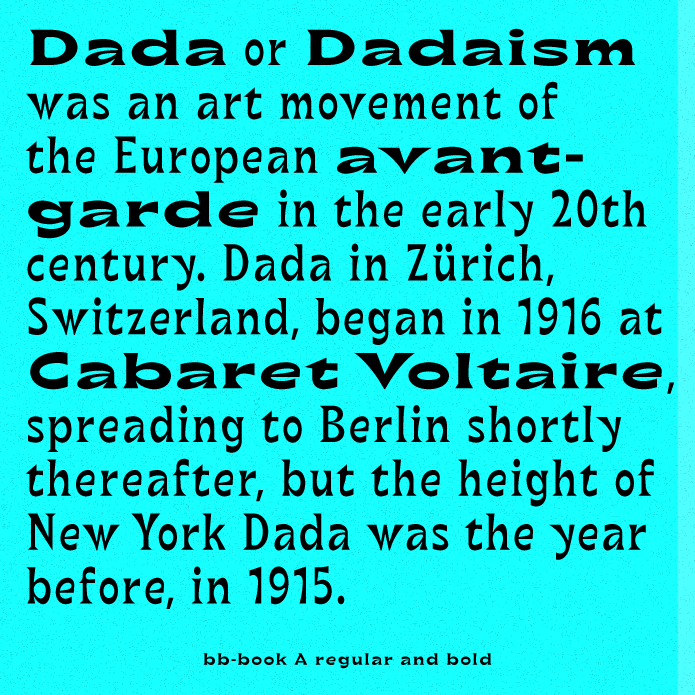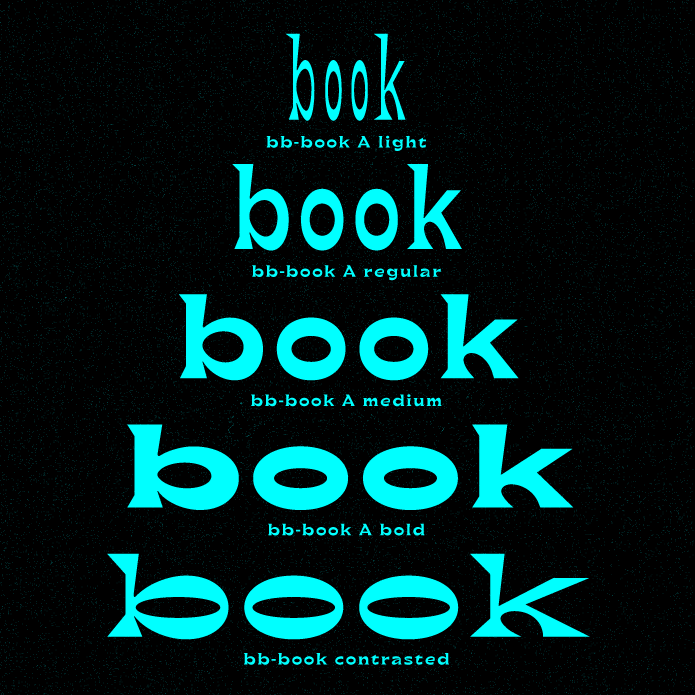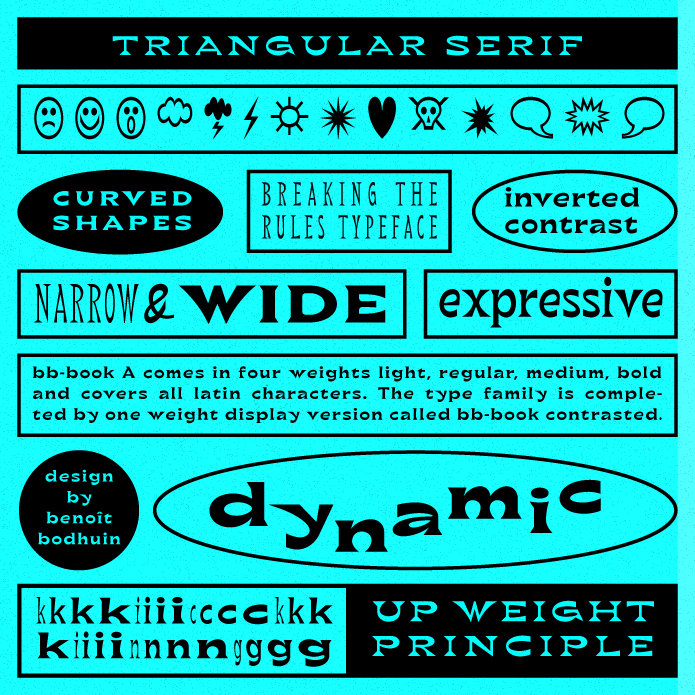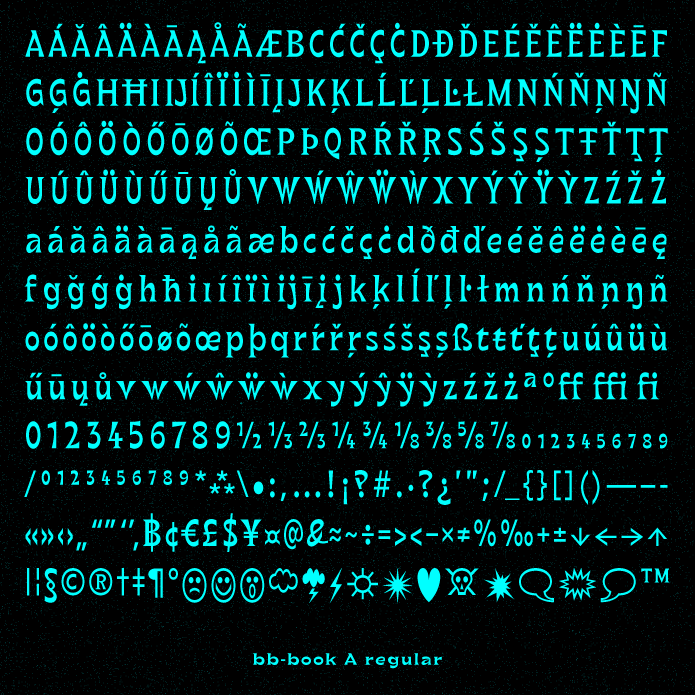
bb-book A und bb-book contrasted
Benoît Bodhuin startet mit seiner neuen Textschrift bb-book A ins Frühjahr 2017. Die Schrift ist bei VolcanoType erschienen und zeichnet sich durch kräftige, dreieckige Serifen und einer Bandbreite an Weiten und einem umgekehrten Strichstärkenkontrast aus. Ergänzend gibt es einen Display Schnitt, bb-book contrasted, welcher die Schriftfamilie vervollständigt. Einzelschnitte sind bereits ab 45,- Euro bei VolcanoType erhältlich.
Benoît Bodhuin über bb-book A: “The light weight is really narrow on the one hand side, the bold weight is really wide on the other hand side. A kicking up weight principle. The inverted contrast of Benoît Bodhuin’s bb-book A stands in the tradition of Roger Excoffon’s Antique Olive.”
Darüber wundere ich mich auch gerade … ein Buch möchte ich aus dieser Schrift jedenfalls nicht gesetzt sehen :shock:
Zumal die Einordnung der Schnitte in verschiedene Schriftgewichte doch recht seltsam ist. Ich hätte das eher in verschiedene Weiten als Condensed, Regular, Semiexpanded und Expanded einsortiert, und die Copntrasted wäre dann wohl eher eine Expanded Light.
und dann ist das eben eine Displayschrift.
Es ist natürlich keine »klassische Textschrift« und sicher auch nicht für eine klassische Anwendung geeignet. Sie ist aber dennoch als Textschrift einzuordnen, denn sie kann als solche unbedingt eingesetzt werden in einem zeitgenössischen Kontext.
Ich würde sie auch für noch so zeitgenössische Texte nicht als "Massentext-Leseschrift" empfehlen. Für mein gefühl einzig Displayschrift.
Macht sie/er ja nicht. Sie ist nur eine Textschrift. Halt, warte: Wie nennt man eigentlich Schriften, die für Texte ungeeignet sind, weil sich Sprache mit ihrer Hilfe nicht fixieren lässt? Symbolschriften? :-D
Diese Einordnung halte ich auch für sehr bedenklich.
Und letztlich ist eine Einstufung in Displayschriften ja keine Herabsetzung.
Klassische Textschriften wie diese hier sind ja praktisch die Arbeitstiere, Robust, unauffällig und eifrig bringen sie lange Texte an den Mann, ohne dem Leser dabei wirklich aufzufallen und hoffentlich nur das Gefühl vermitteln., dass der Text gut aussieht und sich leicht lesen lässt.
Während die Displayschriften in diesem Vergleich eher die Zirkuspferde sind. Hier schafft nicht der Text das Gefühl. sondern die Schrift stülpt dem Text die Gefühlsebene auf.  Das macht sie ja z.B. in der Werbung so interessant, da ein und der selbe Text in stilistisch anderen Schriftarten auch völlig andere Aussagen übermittelt. Genau das ist bei den Arbeitspferden ja nicht gewünscht.
jawoll … keine Textschrift heißt ja nicht daß man der Type gleich ans Leder will ;-)